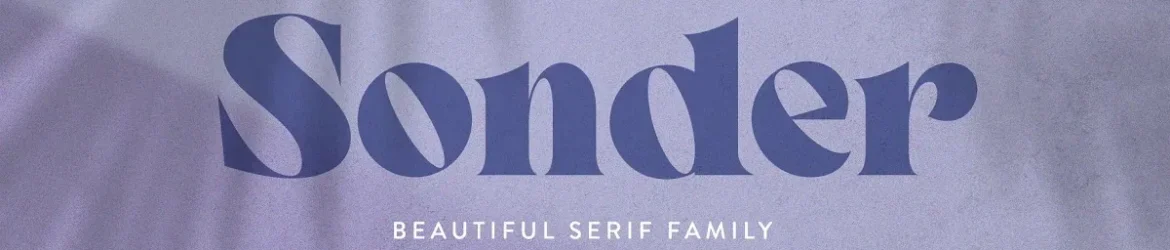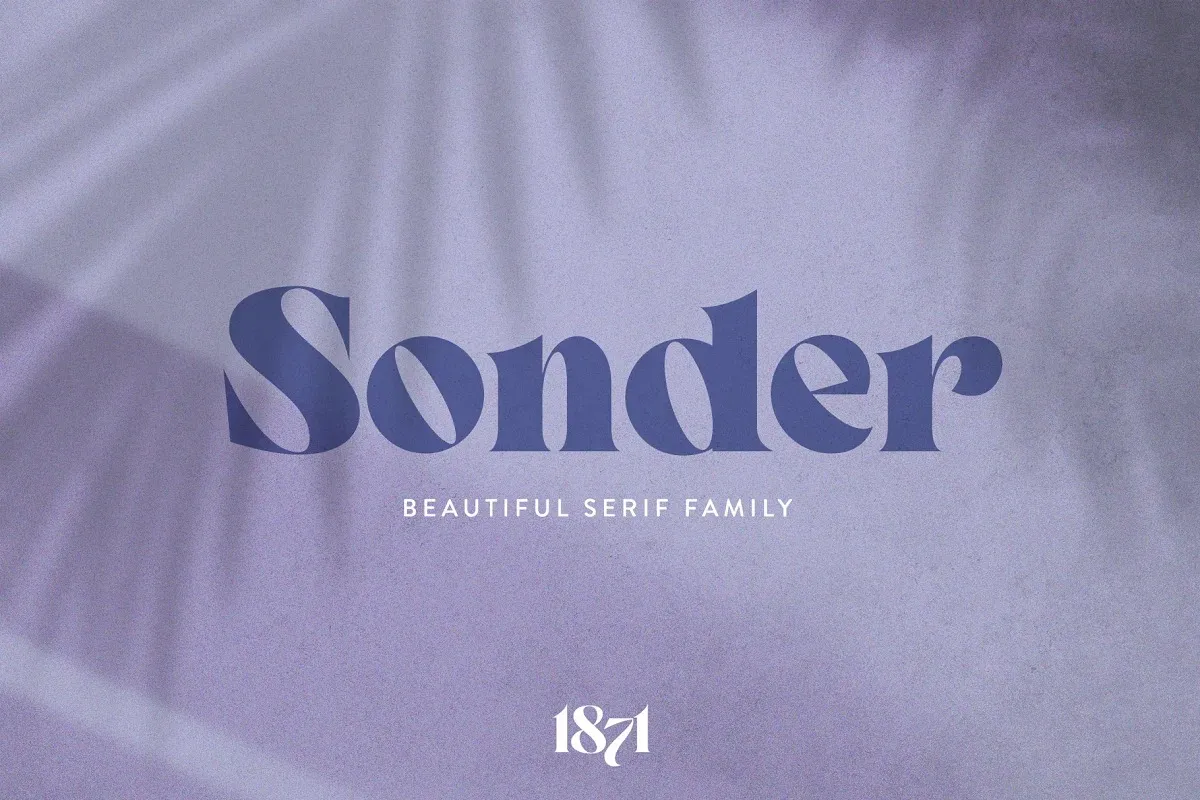
Sonder Font – Fonte Grátis
Sonder Font
A Sonder Font é uma fonte serif contemporânea com cinco pesos que a torna extremamente versátil para qualquer projeto! Inspirada nos pacotes antigos e esquecidos, ela leva ao design um toque de elegância e modernidade. Com sua variedade rica em alternativas estilísticas e caracteres únicos, a Sonder é uma fonte poderosa que se destaca não apenas nas identidades visuais e selos de empresa, mas também nos cartazes, camisetas e outras mídias onde o design precisa ser forte e atraente. Inspirada em paletas de cores vintage e arquitetura clássica, Sonder é ideal para criações que valorizam a simplicidade do bom gosto combinado com a modernidade revigorante.